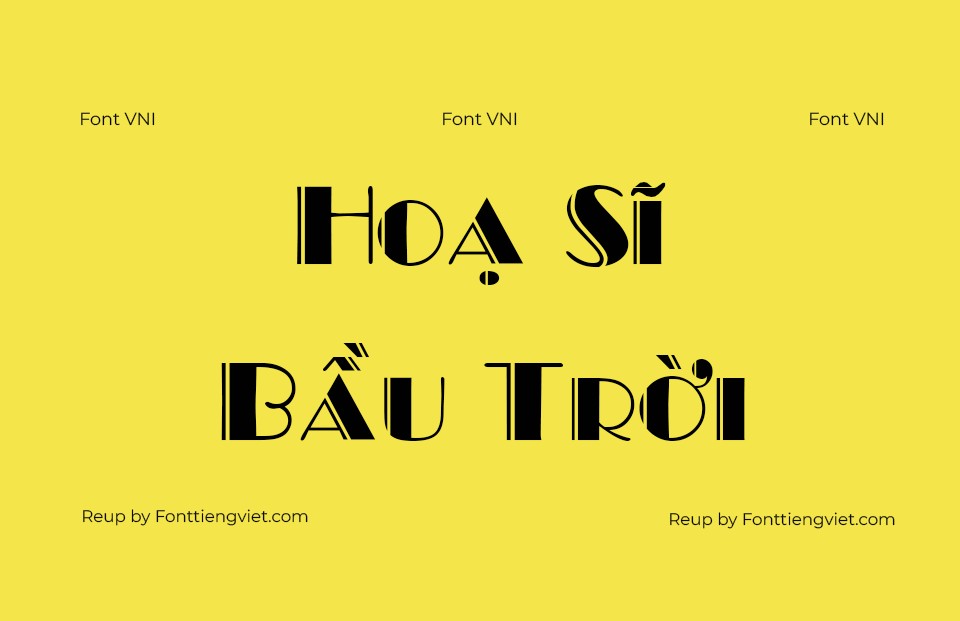
Font Việt hoá VNI Top
Trong thế giới thiết kế đồ họa tại Việt Nam, việc lựa chọn một bộ Font Việt hoá VNI Top chất lượng luôn là ưu tiên hàng đầu của các bạn học sinh và thầy cô giáo. Đây là giải pháp hoàn hảo để tạo nên những bài thuyết trình ấn tượng hoặc các ấn phẩm học đường đẹp mắt. Khi sử dụng Font Miễn Phí, người dùng không chỉ tiết kiệm chi phí mà còn đảm bảo tính thẩm mỹ cao cho văn bản. Bộ phông chữ này được tinh chỉnh kỹ lưỡng để phù hợp với bảng mã VNI truyền thống, giúp khắc phục hoàn toàn lỗi hiển thị tiếng Việt phổ biến trên các phần mềm cũ.
Ưu điểm vượt trội của bộ Font Việt hoá VNI Top
Khả năng tương thích và đa dạng kiểu dáng
Bộ Font Việt hoá VNI Top nổi bật với sự đa dạng về phong cách, từ những nét chữ thanh mảnh, trang trọng đến các kiểu chữ nghệ thuật uốn lượn. Đối với các bạn học sinh, việc sở hữu bộ sưu tập này giúp việc làm báo tường hay thiết kế bìa tiểu luận trở nên chuyên nghiệp hơn bao giờ hết. Đặc biệt, các phông chữ này hoạt động cực kỳ ổn định trên hệ điều hành Windows và các ứng dụng văn phòng phổ biến như Word hay PowerPoint.
Lời kết về ứng dụng phông chữ trong học đường